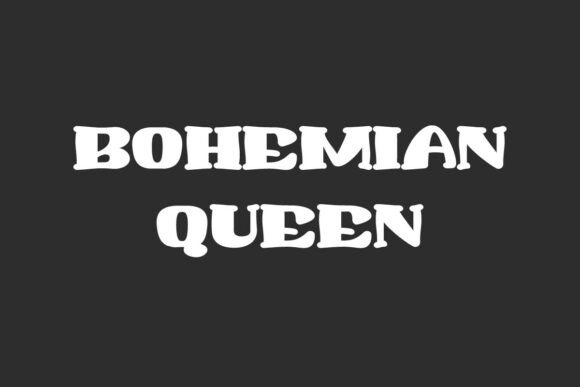
Bohemian Queen
หากคุณกำลังมองหาเนื้อหาคุณภาพสูงเช่น Bohemian Queen แพ็คเกจพรีเมียมนี้เป็นตัวเลือกที่ยอดเยี่ยมสำหรับโปรเจ็กต์สร้างสรรค์ของคุณ
สร้างขึ้นอย่างแม่นยำ Bohemian Queen ให้เวกเตอร์ที่สะอาด พิมพ์ตัวอักษรที่ราบรื่น และใบอนุญาตเชิงพาณิชย์เพื่อความสบายใจ
ไม่ว่าคุณจะสร้างผลิตภัณฑ์ POD (Print on Demand) คำเชิญงานแต่งงาน หรือกราฟิกโซเชียลมีเดีย Bohemian Queen ก็เหมาะสมอย่างยิ่ง